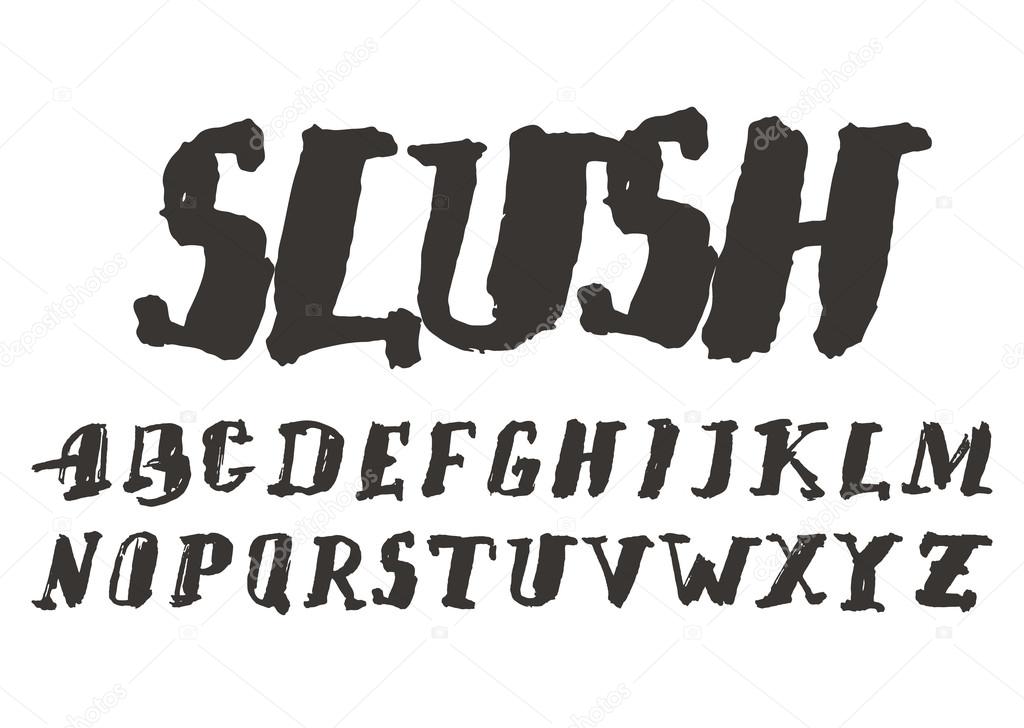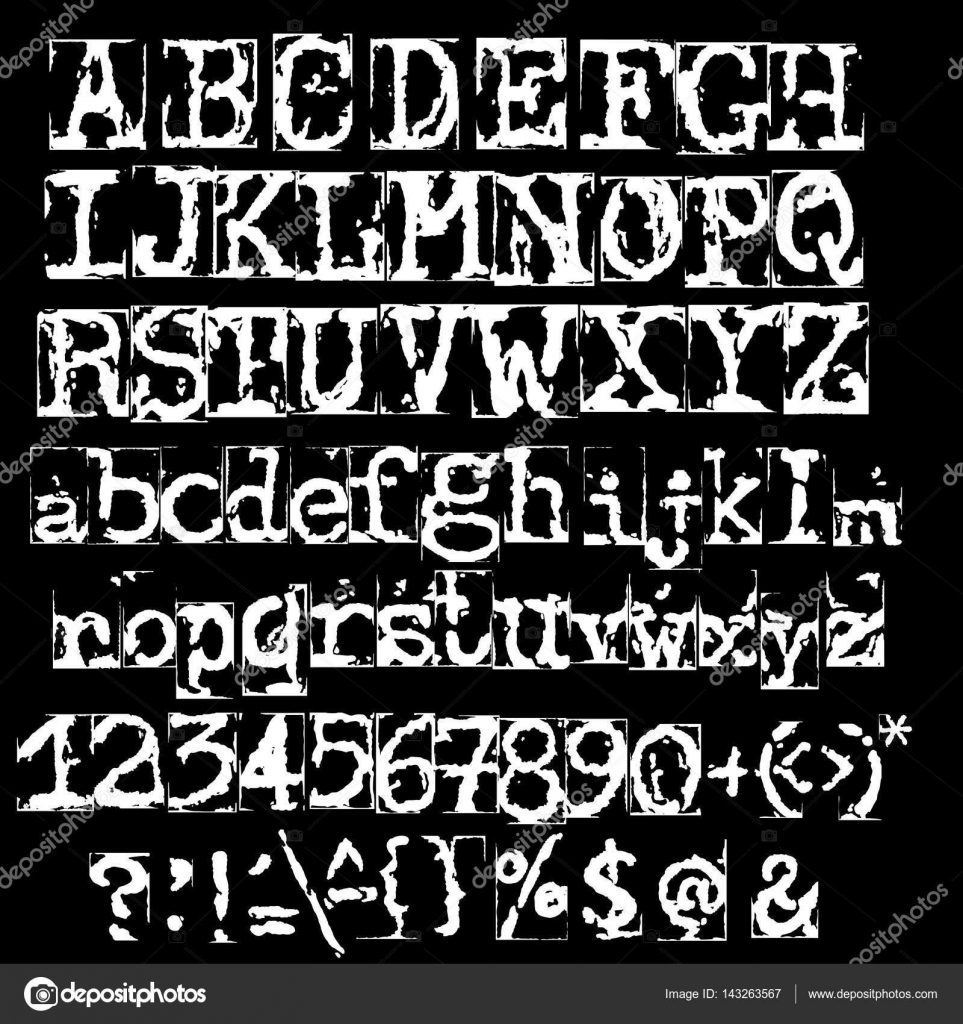
Шрифт гранжевый кириллица: Grunge — каталог бесплатных шрифтов, которые Вы можете скачать
55 бесплатных и платных гранжевых шрифтов для крутого дизайна
Гранж сейчас на волне популярности. Почему? Вероятно, потому, что это противоречит принятым и обычным формам дизайна. Или, может быть, кто-то склонен бросать вызов этим старым, замкнутым веб-стандартам и оспаривать рутинный подход к разработке. Во всяком случае, гранж не выбивается из серой массы. Он привносит творческое сочетание элементов дизайна и типографики, чтобы передать и максимизировать определенное чувство бунта.
Топ 20 платных гражевых шрифтов
Топ 35 бесплатных гранжевых шрифтов
Гранж, грязная, причудливая типографика выделяется среди других стилей шрифтов.
И в обзоре ниже предлагает вам огромную коллекцию бесплатных гранжевых шрифтов. Здесь вы найдете несколько очень хорошо продуманных стилей типографики в стиле гранж с мощным текстурным оформлением. Городские и старомодные, с потрепанным, потертые или в пятнах — эти бесплатные шрифты наверняка дополнят великолепный гранжевый дизайн. Подумайте о своем уникальном подходе к логотипу, веб-дизайну или графическому дизайну с помощью этих универсальных гранжевых шрифтов.
Всем неравнодушным к экспериментам и программированию — крайне рекомендую. 🙂
И сразу на гитхабе! Мне кажется, тут самое ценное — как программировать, этот проект можно использовать как библиотеку эффектов.
Мультижанровый Relaate, теперь с кириллицей
Александр Слобженинов (автор шрифта Grafier из нашей библиотеки tomorrow) выпустил обновления для своего акцидентного Relaate. Со времён первоначального релиза на Future Fonts проект заметно расширился — тогда это была только злая антиква, а теперь и замысловатый рукописный гротеск, и широкий египетский шрифт.
В последней версии добавились пять жирностей для антиквы и кириллица — для всех начертаний.
Story Brush — это шрифт кисти с высокой детализацией, имеющий поверх глифов. Поставляется с 2 Verison Regular и Slanted. Этот шрифт оснащен функцией OpenType для индивидуального восприятия вашего дизайна.Отлично подходит для ваших новых творческих проектов. Playlist — это совершенно несовершенный шрифт, нарисованный от руки, с использованием стилей сухой кисти. Шрифт плейлиста содержит 3 стиля: Script, Caps и Ornament, которые вы можете комбинировать для создания красивых дизайнов. Abys был создан 3 года назад Иоаной Архонтаки а. Parabola — это рукописный шрифт с большой индивидуальностью, он отлично подходит для любого проекта и придает индивидуальный подход ко всему, что вы делаете.